تغییر فونت واتساپ چگونه است؟ کاربران زیادی نمیدانند که امکان تغییر فونت در واتس اپ وجود دارد. واتساپ در سیستمعامل اندروید از همان فونتی که در تنظیمات استفاده کردهاید کمک میگیرد و در iOS هم از همان فونت پیشفرض استفاده میکند. ولی عوض کردن فونت در واتساپ به چند طریق امکانپذیر است.
واتساپ یکی از محبوبترین پیامرسانهای دنیاست اما آیا شما با تمام ترفندهای آن آشنا هستید؟ یکی از این ترفندها امکان تغییر فونت واتساپ در ایفون و اندروید به یک فونت دیگر است. با این ترفند میتوانید پیامهایتان را بهشکل شخصیسازی شده و متفاوتی برای مخاطبین خود ارسال کنید. اما تغییر رنگ یا فونت واتساپ وب و نسخه گوشی آن چگونه انجام میشود؟
آموزش تغییر فونت واتساپ
واتساپ چند سالی است امکان استفاده از چند فونت متفاوت را در چتها میدهد. تغییر فونت در واتساپ جی بی و اکثر نسخههای مشابه به نسخه اصلی نیز فرایند یکسانی دارد. البته تعداد فونتها محدود است و به همین خاطر انتظار تغییر فونت به نستعلیق را در واتساپ نداشته باشید. با این حال میتوانید شکل و ظاهر فونت پیشفرض را با تغییرات جالبی همراه کنید.
1. پررنگ کردن کلمات
شاید اولین سوالی که برایتان پیش بیاید این است که اصلا فونت واتساپ کلمات کجاست؟ واتساپ گزینه جداگانهای برای تغییر یا انتخاب فونت ندارد. شما باید با استفاده از کاراکترهای خاص فونت را تغییر دهید. اولین کاری که برای تغییر فونت گوشی در واتساپ میتوانید انجام دهید، پررنگ کردن کلمات است.
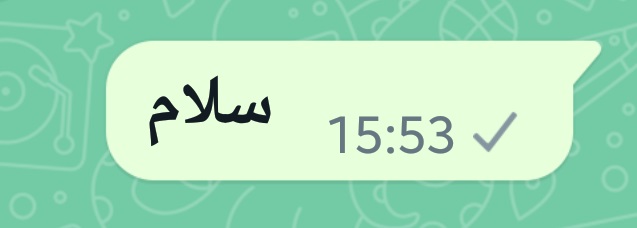
برای انجام مراحل عوض کردن فونت واتساپ، ابتدا واتساپ را باز کنید و به یکی از چتها بروید. حالا پیامتان را مثل همیشه تایپ کنید. در مرحله بعدی کافی است که در ابتدا و انتهای پیام یک کاراکتر * قرار دهید. مثلا پیام ما سلام است. برای آنکه این کلمه را پررنگ کنیم، آن را به این شکل مینویسیم:
*سلام*
حالا دکمه ارسال را بزنید. همانطور که در تصویر میبیید پیام ما بصورت بولد یا پررنگ نشان داده میشود. این یکی از روش های عوض کردن فونت واتساپ است.
2. فونت ایتالیک
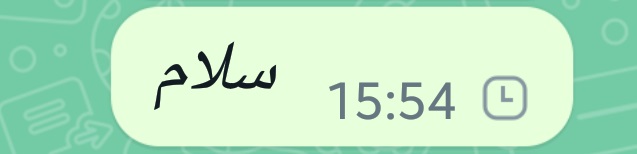
ترفند تغییر فونت دیگری که هم در نسخه واتس اپ اصلی و هم بیزنس میتوانید استفاده کنید بهشما اجازه کج کردن یا ارسال کلمات بصورت ایتالیک را میدهد. برای استفاده از این ترفند و قالب بندی متون به این شکل در واتساپ، دوباره یک صفحه چت را باز کرده و اینبار بین اول و آخر پیامتان کاراکتر _ را قرار دهید. به این صورت:
_سلام_
وقتی پیام را ارسال کنید، متن شما بصورت کج نمایش داده خواهد شد.
3. خط خوردگی یا فونت Strikethrough
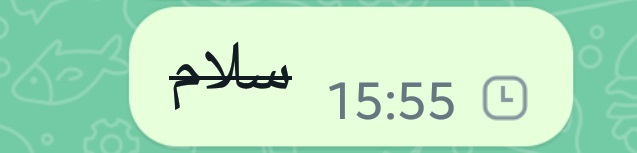
با این ترفند تغییر فونت متن در واتساپ، میتوانید یک خط روی پیامی که ارسال میکنید بکشید. برای ارسال پیام در این حالت، اینبار باید اول و آخر متن کاراکتر ~ را اضافه کنید. به این صورت:
~سلام~
4. فونت مونواسپیس
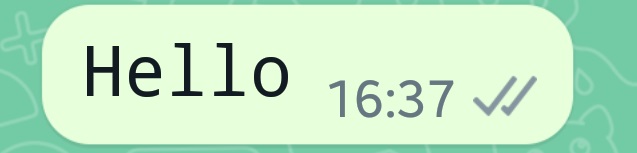
چگونه در واتساپ فونت را عوض کنیم؟ با این ترفند میتوانید پیام را با یک فونت دیگر ارسال کنید. البته این یک مورد برای تغییر فونت فارسی در واتساپ فایده ندارد و بیشتر برای پیامهای انگلیسی است، چرا که پیامهای فارسی تغییر چندانی نسبت به فونت پیشفرض ندارند. برای استفاده از فونت مونواسپیس، ابتدا و انتهای پیام باید 3 کاراکتر ` قرار دهید. آموزش تغییر فونت واتساپ به این شکل است:
“`سلام“`
5. ترکیب پررنگی، ایتالیک و خط خوردگی
چگونه فونت واتساپ را ایفون کنیم؟ یکی دیگر از راههای تغییر فونت های واتساپ و تغییر فونت واتساپ جی بی امکان ترکیب 3 حالت اول با هم است. میتوانید با این روش، متن پیام را به 3 حالت پررنگ، ایتالیک و خط خورده ارسال کنید. چگونگی تغییر فونت واتساپ در این حالت هم مثل بالا است با این تفاوت که باید هر 3 کاراکتر مربوط به این حالتها را به ترتیب استفاده کنید. به این شکل:
~_*سلام*_~
تغییر رنگ فونت واتس اپ
چگونه فونت واتساپ را تغییر دهیم؟ برای تغییر رنگ باید از برنامه های تغییر فونت واتساپ استفاده کنید چرا که داخل خود برنامه چنین امکانی وجود ندارد. همچنین این قابلیت فقط مخصوص کاربران اندروید است. یعنی فقط بصورت اندروید به اندروید میتوانید فونتها را با رنگ متفاوت ارسال کنید. کاربران iOS قادر به دریافت رنگهای اضافی در برنامه تغییر فونت واتساپ نیستند.
برای تغییر رنگ، اپلیکیشن تغییر فونت در واتس اپ وجود دارد که میتوانید از آنها کمک بگیرید. مثلا برنامه Blue Words بهشما این امکان را میدهد تا کلمات را به رنگ آبی در واتساپ تایپ کنید. علاوه بر این امکان استفاده از فونتهای مختلف این برنامه در سایر شبکههای اجتماعی مثل اینستاگرام و تیکتاک هم وجود دارد.
تغییر فونت استاتوس واتساپ
چگونه فونت واتساپ جی بی را تغییر دهیم؟ افزون بر این، امکان تغییر و عوض کردن فونت استوری واتساپ هم وجود دارد. البته فونت فارسی در استاتوس با این روش تغییر چندانی نمیکند. اما میتوانید فونت کلمات و عبارات انگلیسی را تغییر دهید و از حالت پیشفرض استفاده نکنید. برای انجام اینکار فقط کافی است در زبانه Status روی آیکون مداد بزنید.
سپس پیامتان را تایپ کنید و بعد از پایین سمت چپ صفحه روی آیکون T بزنید. هربار که این آیکون را لمس کنید، فونت وضعیت واتس اپ شما تغییر پیدا میکند.
سوالات متداول
1. چگونه فونت واتساپ را ایفون کنیم؟
بصورت پیشفرض و از داخل خود برنامه امکان انجام چنین کاری وجود ندارد، با این حال میتوانید از برنامههای متفرقه تغییر فونت برای انجام اینکار استفاده کنید.
2. چگونه فونت واتساپ را نستعلیق کنیم؟
تغییر فونت در واتس اپ به نستعلیق هم امکانپذیر نیست. واتساپ اصلا از فونتهای فارسی پشتیبانی نمیکند و فقط چند فونت انگلیسی در این برنامه قابل استفاده هستند که در این مطلب به آنها اشاره کردیم.
چگونه فونت واتساپ را نستعلیق کنیم؟ تغییر فونت واتس اپ همانطور که دیدید کاری است که با چندین کاراکتر اضافی بهراحتی قابل انجام است. البته نحوه انجام اینکار خیلی راحت نیست و هربار ممکن است وقت زیادی از شما بگیرد. علاوه بر این برنامههای متفرقه زیادی هم برای عوض کردن فونت در واتساپ وجود دارند که میتوانید از آنها کمک بگیرید.